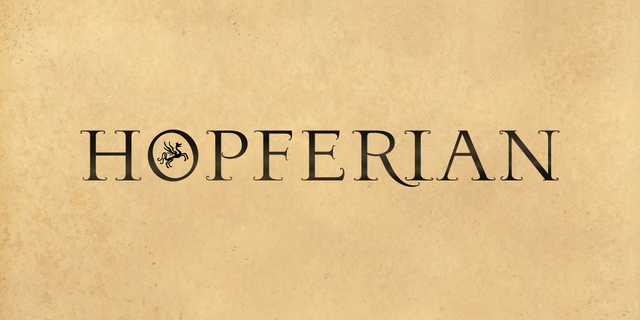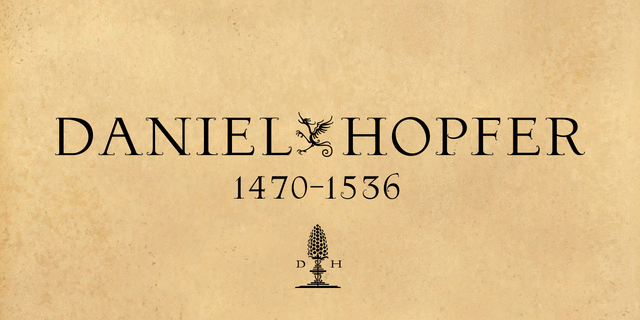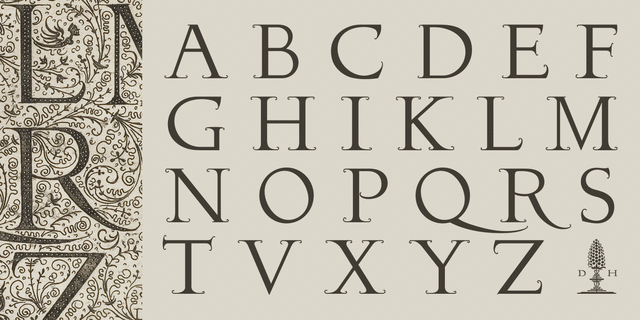
Шрифт Hopferian разработан на основе гравюр немецкого художника Даниэля Хопфера (1470-1536). При создании шрифта авторы старались сохранить архаику и некоторое несовершенство присущее прототипу, чтобы подчеркнуть его характерный шарм. Причудливые завитки на засечках придают шрифту сказочности и игривости. Гарнитура включает начертания с точками, как в оригинале Хопфера. Цифровая версия шрифта разработана Лукьяном Турецким, Марией Сокол в студии 2D Typo в 2013 году.
героический ,
утонченный ,
красивый ,
выразительный ,
характерный ,
эпический ,
звонкий ,
легендарный ,
прекрасный ,
монументальный ,
средневековый ,
ажурный ,
легкий ,
наивный ,
пафосный ,
праздничный ,
романтичный ,
динамичный ,
горячий ,
огненный ,
артизанальный ,
крафтовый